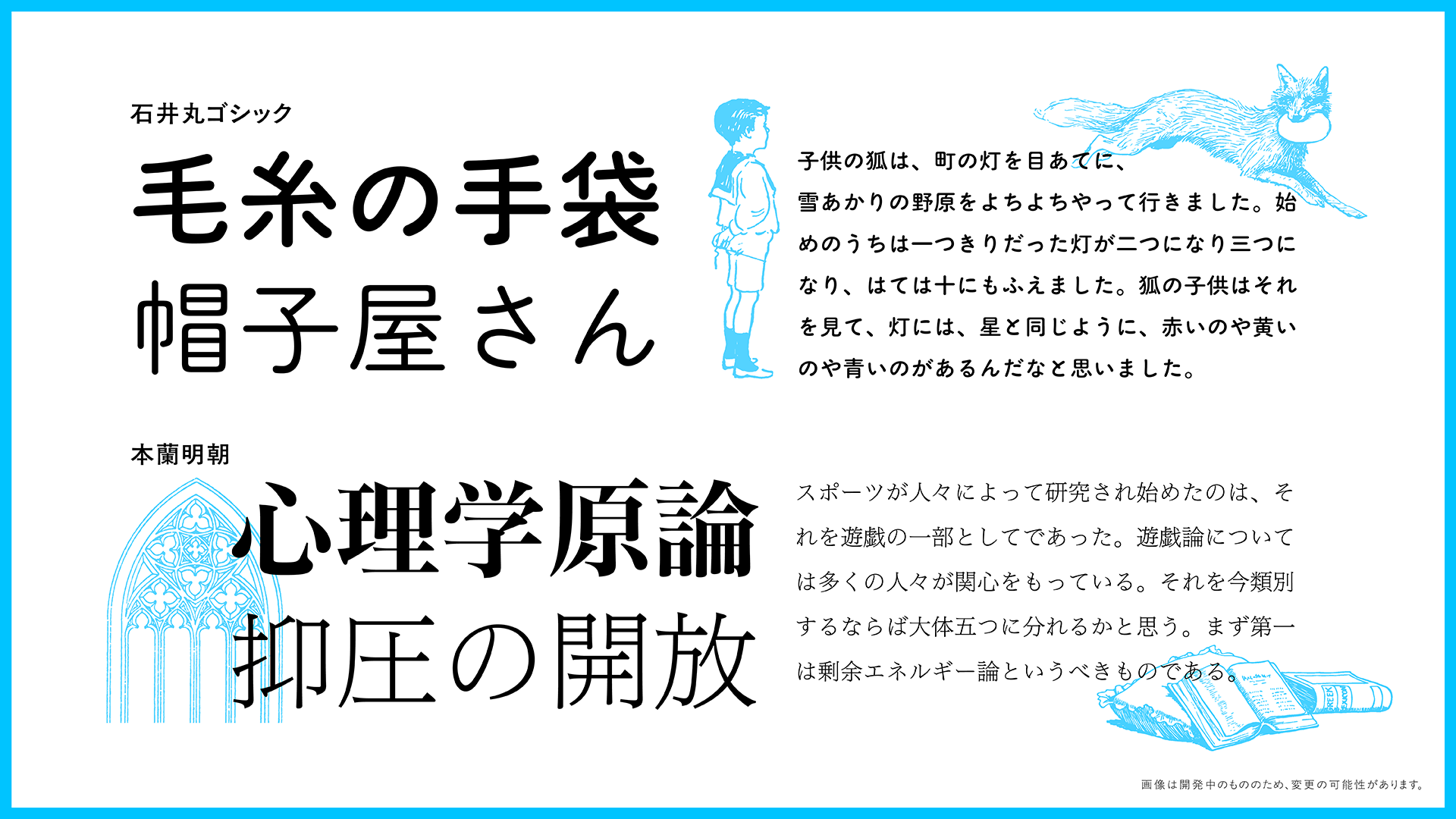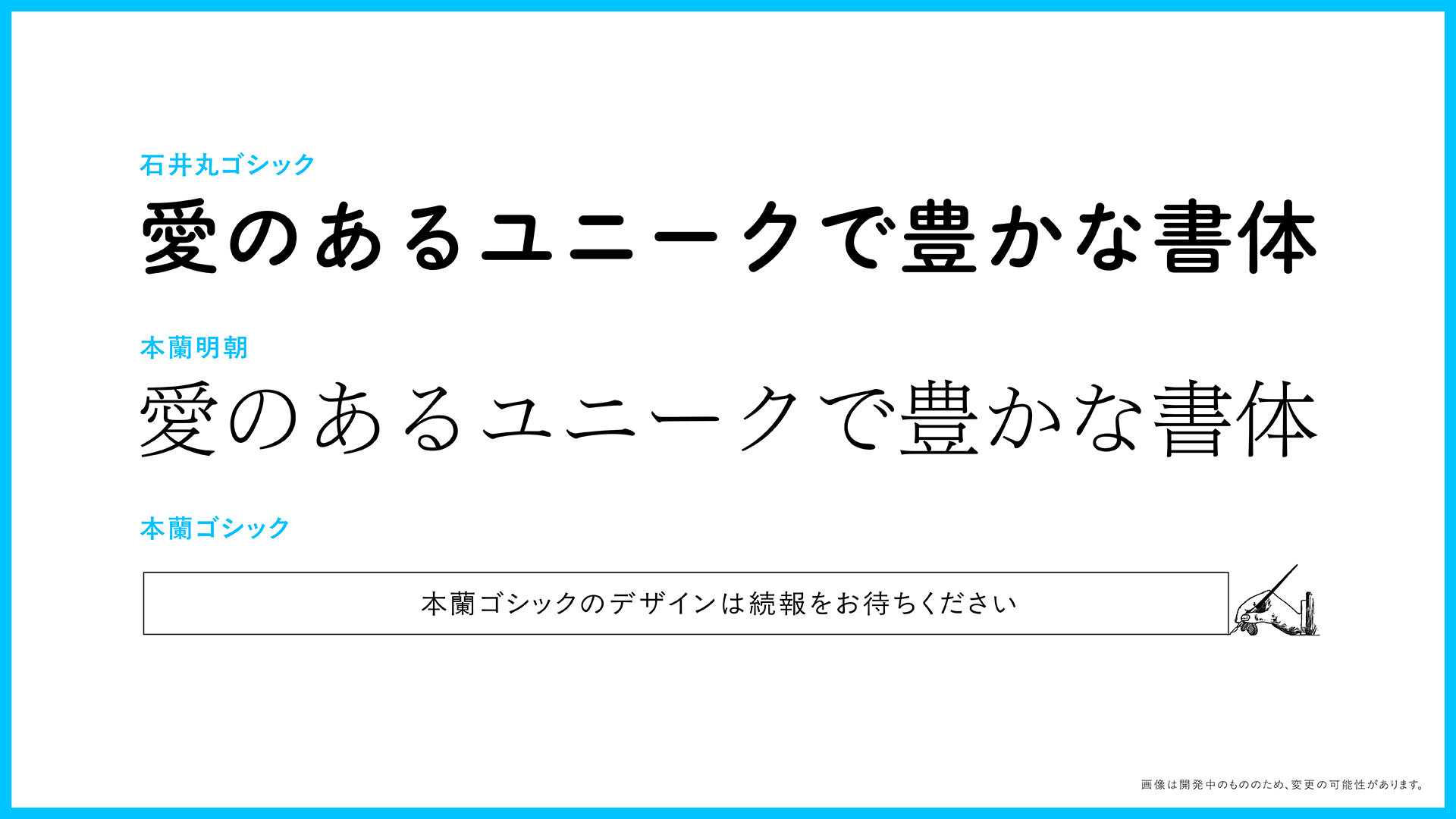
モリサワ 開発中の写研改刻フォント「石井丸ゴシック」「本蘭明朝」「本蘭ゴシック」を発表、写研フォントのメイキング動画も公開
改刻フォントは、オリジナルの写研書体が持つ優美さを残しつつ、現代の環境や用途に合わせてリデザインした新しい書体です。写研と、モリサワおよびそのグループ会社である有限会社字游工房(代表取締役:石本馨 本社:東京都新宿区下宮比町2-27、以下字游工房)の3社共同体制で開発を進めているもので、全体監修は、写研出身であり現在は字游工房の書体設計士である鳥海修氏が務めています。2024年10月には、改刻フォントの第1弾として「石井明朝」「石井ゴシック」をリリースしました。
そしてこの度発表する改刻フォントは、写研の創業者・石井茂吉氏がデザインしたクラシックな丸ゴシック体「石井丸ゴシック」、明瞭なデザインの中に伝統的な筆のニュアンスを感じさせるモダンスタイルの明朝体「本蘭明朝」、本蘭明朝と対になる書体として開発された、ニュートラルなデザインの「本蘭ゴシック」です。
石井丸ゴシックはファミリー展開を見直し、従来の3ウエイトから5ウエイトに拡張するほか、本蘭明朝は現代の表示環境を考慮してコントラストの再検討を行い、さらに使いやすいフォントを目指して改刻します。そして本蘭ゴシックの改刻では、オリジナルの本蘭ゴシックも開発した写研のデザイナーが自ら関わり、かなのリデザインを進めます。
歴史ある写植書体を受け継ぎながら、時代の変化に合わせて改刻し、より完成度を高めたフォントとして次の時代へと伝えていきます。
また、これら改刻フォントのほかにも、写研から提供を受けたアウトラインデータをもとに、不足文字の追加や文字セットなどの仕様を整理した「写研クラシックス」の追加開発も進行中です。
写研書体 OpenTypeフォント化開発プロジェクトについて
写研書体は、写研が提供してきた写真植字機および専用のシステムを通じて、1970年代から2000年前後にかけて広く使用されてきた書体です。今回のOpenTypeフォント化によって、写研書体がPCやタブレットなどの一般的なデバイスでもお使いいただけるようになります。邦文写真植字機発明100周年となる2024年に43フォントの提供を開始し、今後合計100フォントに及ぶラインナップのリリースを予定しています。